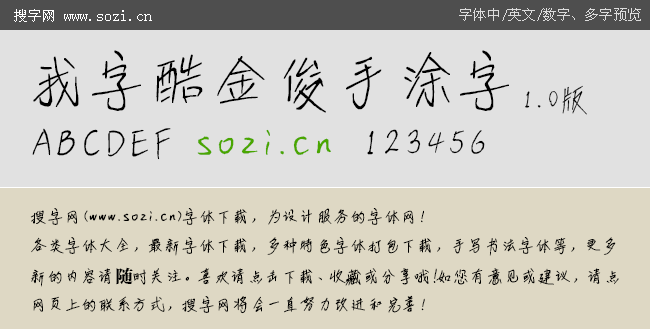
我字酷金俊手涂字
搜字網(wǎng)提供一款我字酷金俊手涂字中文書法字體下載,我字酷金俊手涂字是一款非常漂亮的手寫風(fēng)格書法字體,字體書寫流暢,整體字形瀟灑大方,適合應(yīng)用于廣告設(shè)計(jì)、名片設(shè)計(jì)、包裝印刷、海報(bào)設(shè)計(jì)等應(yīng)用。